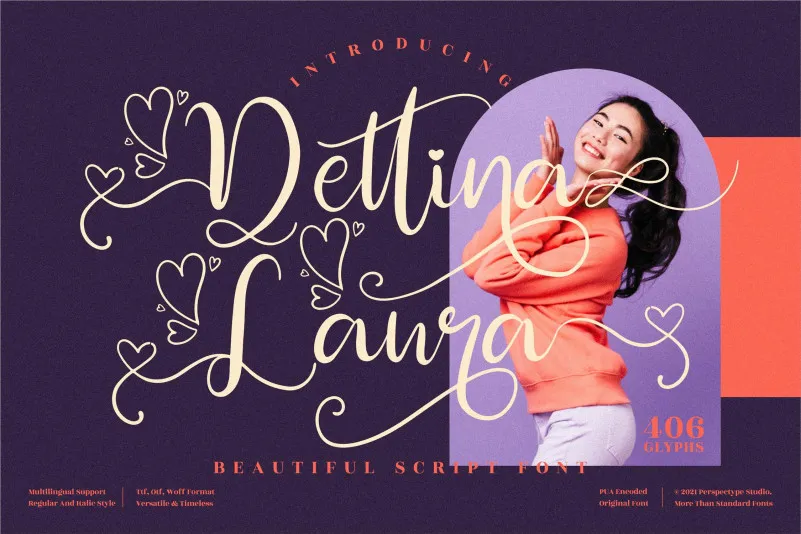
Dettina Laura Font
Dettina Laura é uma linda fóntica tipográfica para escrita entrelaçada com traços delicados. Cada caractere flutua sobre a linha base, criando um efeito de dança que promete adicionar um toque exuberante e sofisticado a qualquer projeto de design que você possa criar. Esta fonte é PUA codificada, o que significa que você terá acesso fácil aos inúmeros caracteres e ligaturas incríveis que ela oferece. Estou em uma categoria de fóntes script, criadas para dar vida a textos com um ar elegante e autêntico. Ideal para quem procura adicionar um toque romântico à sua identidade visual ou personalizar materiais como cartões de aniversário ou editoriais de moda. Com Dettina Laura, você pode transformar simples mensagens em uma arte sofisticada que captura o espírito delicado e elegante da fóntica.